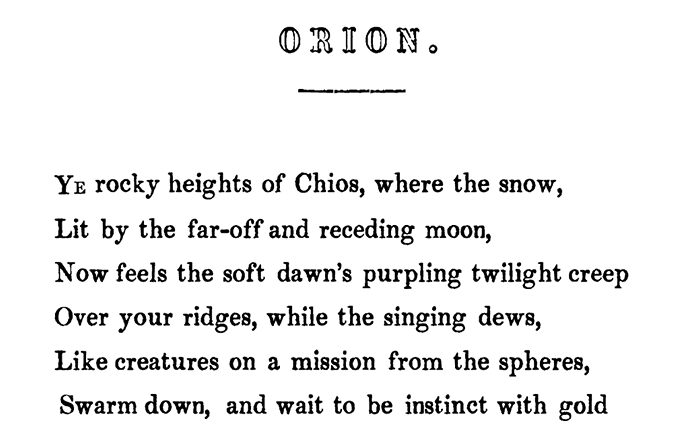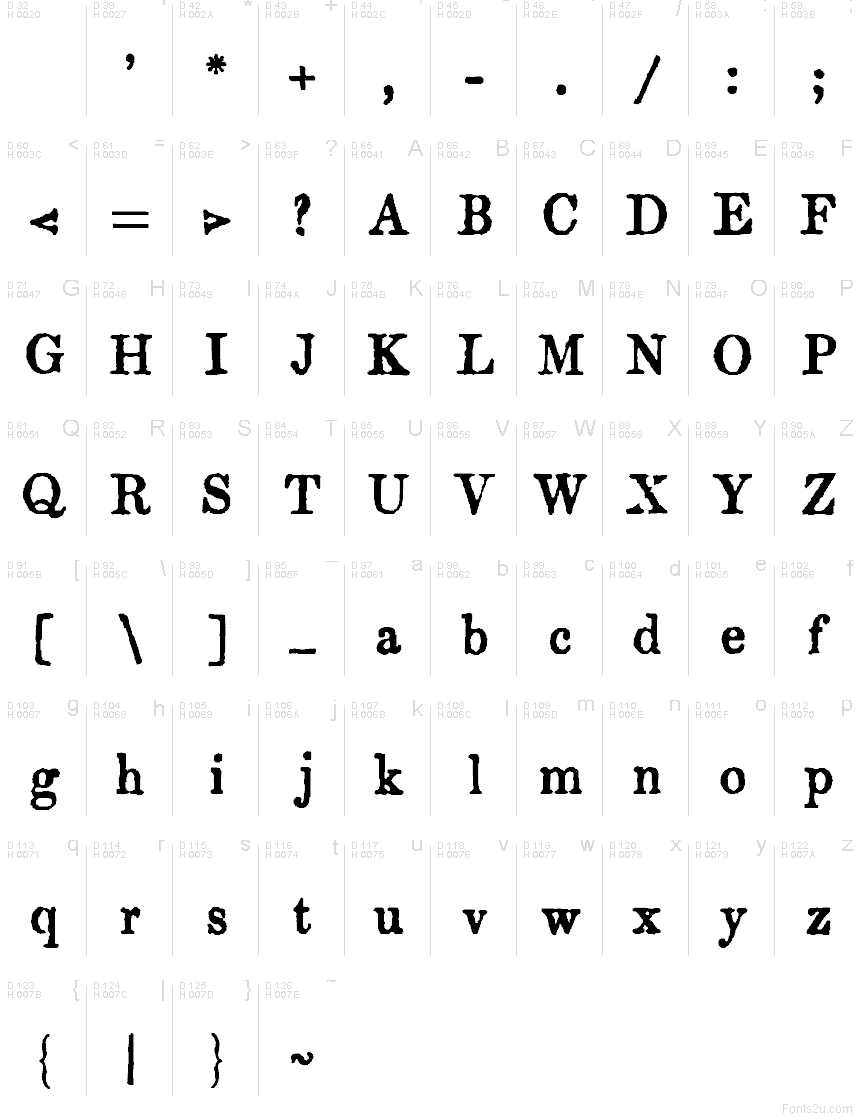
RHHorneOrion
RH Horne Orion je bezplatné display písmo inšpirované eróziou drevených tlačových znakov. Pôsobí drsne a ošúchane. Písmená vyzerajú ako „odhryznuté“ od farby a ľahko obité; vďaka hrubým pätkám, výraznej váhe a drsným okrajom pripomína skôr starú kníhtlač než uhladený moderný font.
Hodí sa na plagáty, knižné obálky, branding pre puby, titulky a obaly, ktoré chcú navodiť zaprášenú atmosféru 19. storočia bez toho, aby pôsobili príliš zdobne. Ako bezplatné písmo funguje najlepšie v krátkych nadpisoch, iniciálach a na obálkach, kde si tieto obité tvary a robustné pätky vystačia s atmosférou samy o sebe.
Font RH Horne Orion je oživením dávno zabudnutého, zastaralého písma z 19. storočia, ktorého autorom je Gary Stephens.